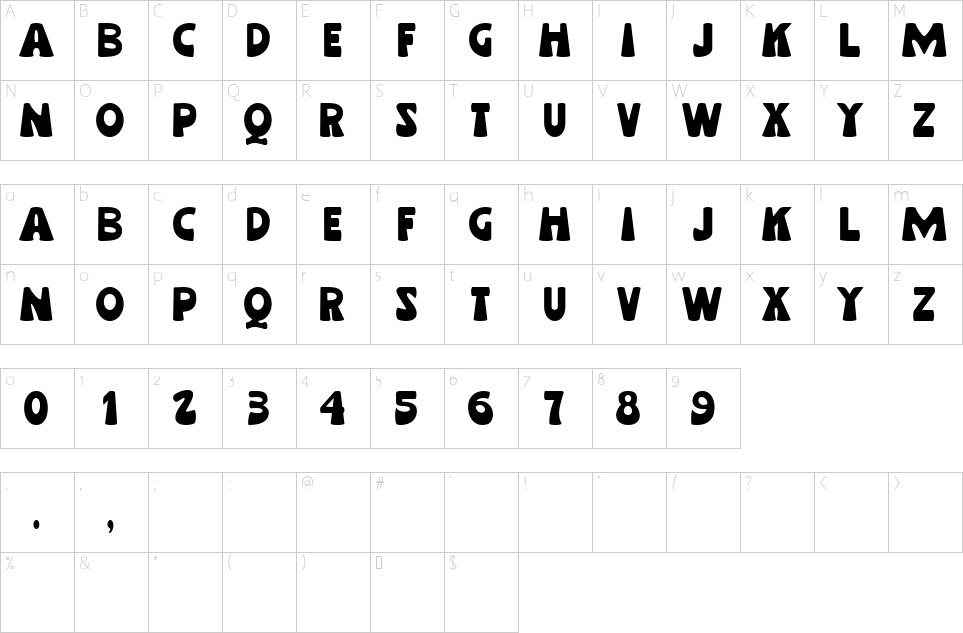
A fonte Phoen oferece uma experiência de escrita envolvente e natural, perfeita para designers e criativos que buscam uma opção de fonte grátis. Desenvolvida por Canden Meutuah, a Phoen foi projetada para combinar elegância e facilidade de uso. Esta fonte tem sido uma opção popular entre designers que valorizam características sólidas e uma aparência fluida, tornando-se um ícone na categoria de fontes gratuitas. Com seu design minimalista e seu amplo rango de usos, a Phoen pode se adaptar a qualquer projeto, seja para criação de materiais digitais, como sites e aplicativos, ou para trabalho com impressão, como editoriais e materiais de mídia. Com uma aparência única e uma variedade de opções de estilo, a Phoen é uma escolha ótima para qualquer designer que está procurando por uma fonte de qualidade que seja fácil de usar e totalmente gratuita.